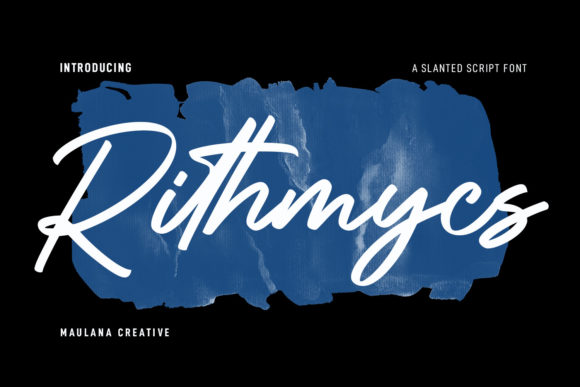
Rithmycs Script Font
Doğru tasarım öğelerini bulmak zor olabilir, ancak Rithmycs Script Font, çalışmanızı anında bir üst seviyeye taşıyan olağanüstü bir koleksiyon sunar.
Hassasiyetle hazırlanan Rithmycs Script Font, temiz vektörler, pürüzsüz tipografi ve içinizin rahat etmesi için ticari bir lisans sağlar.
İster İsteğe Bağlı Baskı (POD) ürünleri, ister düğün davetiyeleri veya sosyal medya grafikleri oluşturuyor olun, Rithmycs Script Font ideal bir uyumdur.